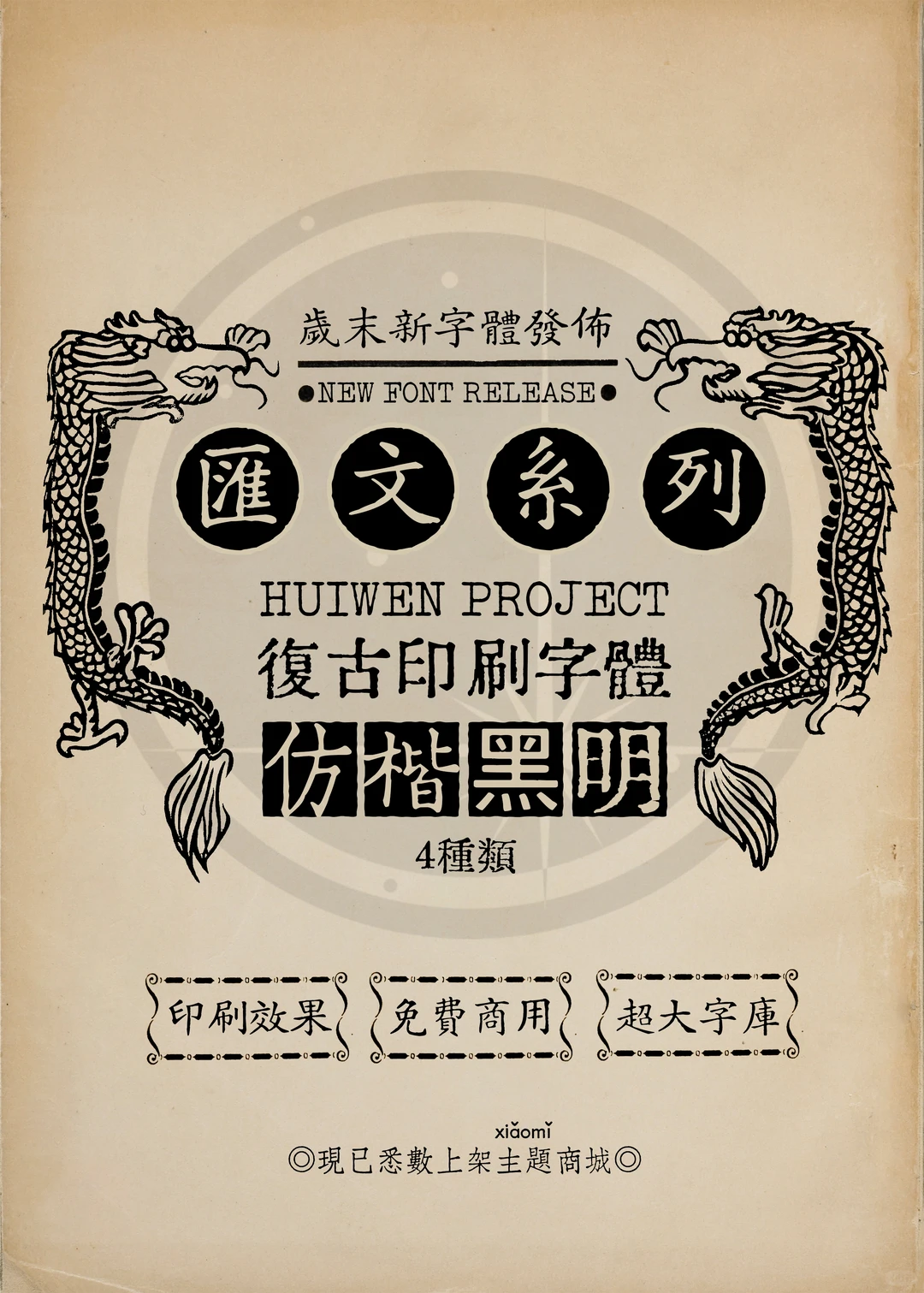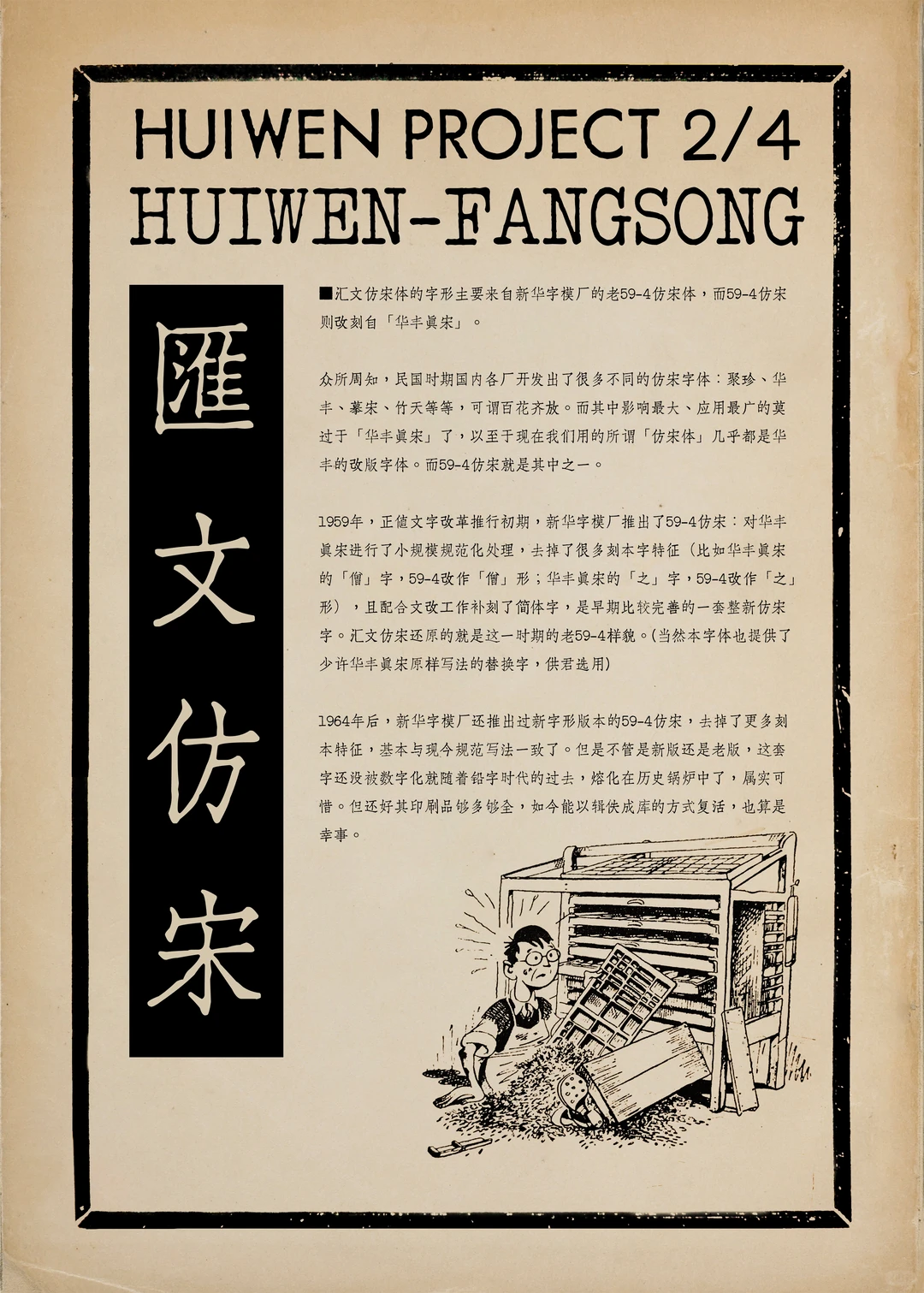
汇文仿宋的字形底子,主要源自新华字模厂早年打磨的老59-4仿宋,而这版59-4本身,则是从「华丰眞宋」重新勾描翻刻而来。明眼人都知道,民国那些年国内各大造字厂可没闲着,陆续弄出了聚珍、华丰、摹宋、竹天等一大批仿宋变体,确实是热闹得很。但要说影响力最大、流通最广的,还得数「华丰眞宋」。到现在大家口中常说的仿宋体,大多都是贴着华丰改款的名头,前头提过的59-4仿宋也在其列。1959年前后,正好撞上文字改革刚起步的阶段,新华字模厂便顺势推出了59-4仿宋。他们对华丰眞宋做了小幅度的规范调整,剔除了不少传统刻本的旧习气(例如华丰原版里的「僧」字,59-4直接换成了「偷」的构形;还有「之」字,也从老写法改成了现在的标准态)。同时紧扣文字改革的要求,往里补齐了配套的简体字形,堪称早期完成度极高的一套新式仿宋字。汇文这次所做的,正是把那个年代老59-4的原生面貌给复原出来。(当然,如果你更钟情华丰真宋原本的结体,字库中也预留了几款原样写法的备用字形,方便你按需切换。)时间来到1964年以后,新华方面又推出了一版带有新字形色彩的59-4仿宋,进一步磨平了刻版痕迹,整体已经相当贴近如今的规范写法。遗憾在于,无论老版还是新版,都未能跨过数字化的门槛,便随着铅字的落幕一并投入历史熔炉,化作铁水流淌而去,实在令人扼腕。幸好当年的印品留存得足够充足完整,如今咱们还能通过广泛搜集旧籍,让这些字符借由建库整理的方式重新归来,倒也是一桩值得欣慰的美事。